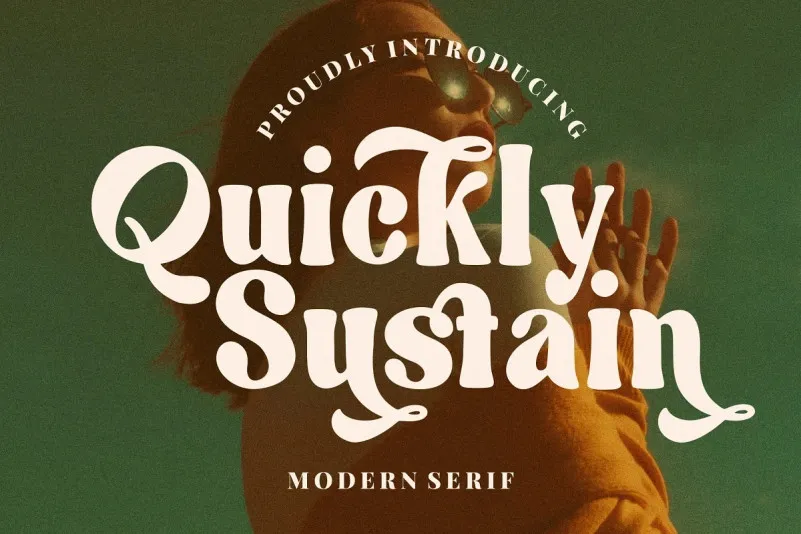
Quickly Sustain Font – Fonte Grátis
Quickly Sustain Font
Esta fonte serif, chamada Quickly Sustain Font, foi criada pela Creatype Studio. Inspirada no estilo Retro, essa fonte perfeita para ambientes de exibição e design de produtos é uma opção ideal para projetos de marca, logomarca, casamentos, publicações em redes sociais, anúncios, embalagens de produtos, designs dos próprios produtos, etiquetas, fotografia, watermark, convites, papelaria e qualquer projeto que exigir um sabor à mão. Rapidamente se sustentar é perfeito para várias aplicações visuais onde você deseja adicionar um toque atraente e distintivo. Seja você designer de arte ou criador de conteúdo online, essa fonte vai ser uma ótima opção. Ela lhe dá o poder de criar designs inovadores e imprimíveis em alta qualidade. Experimente Today!